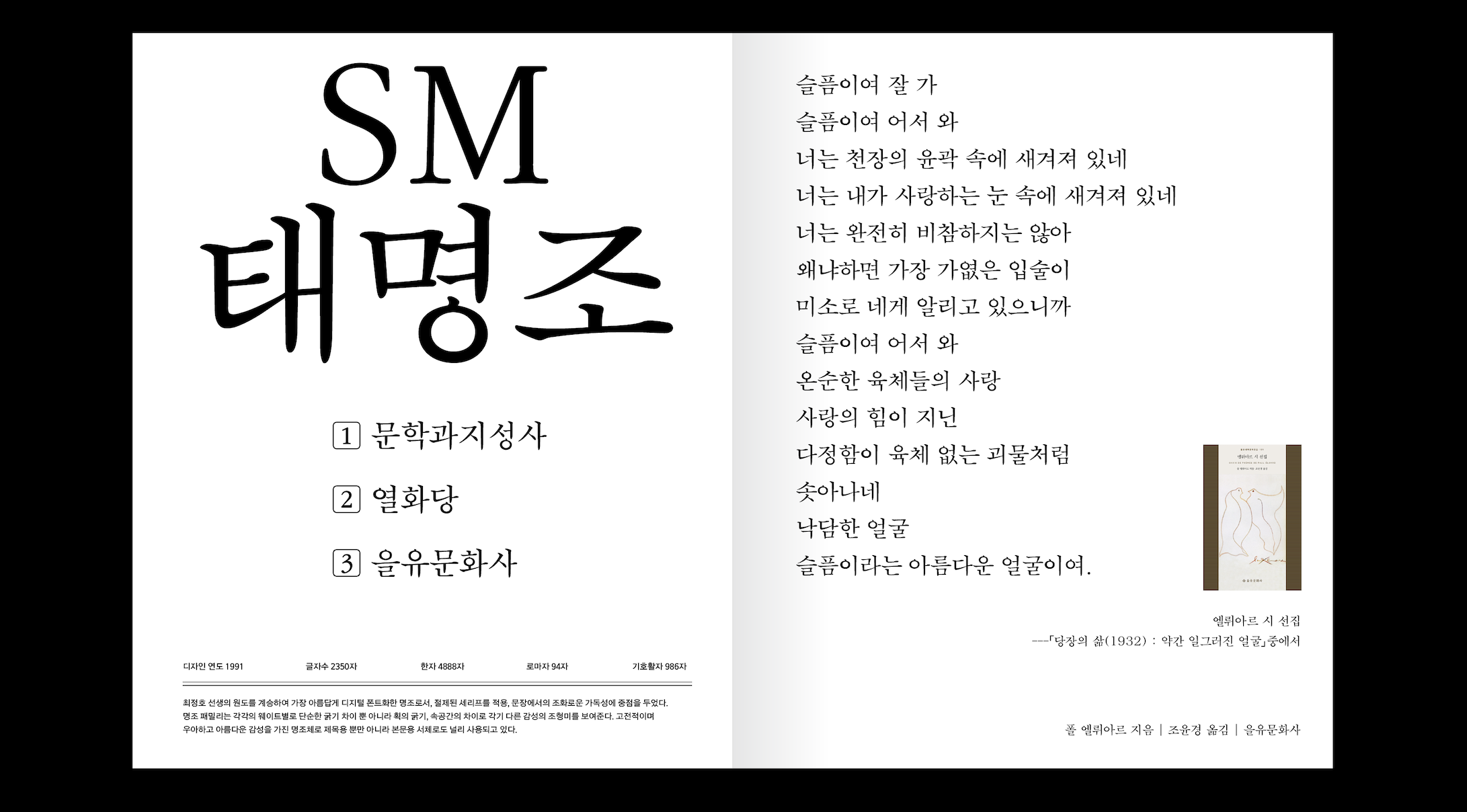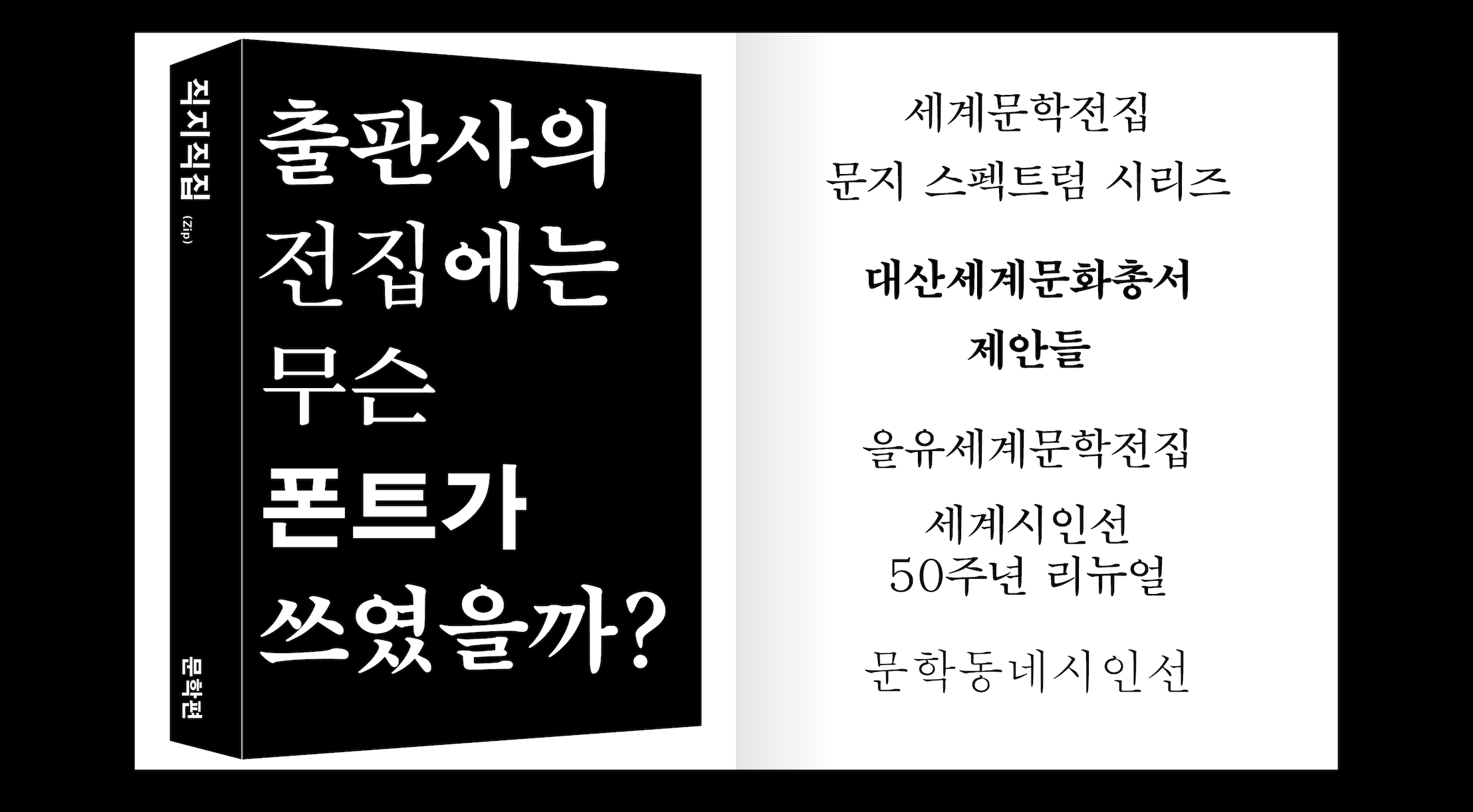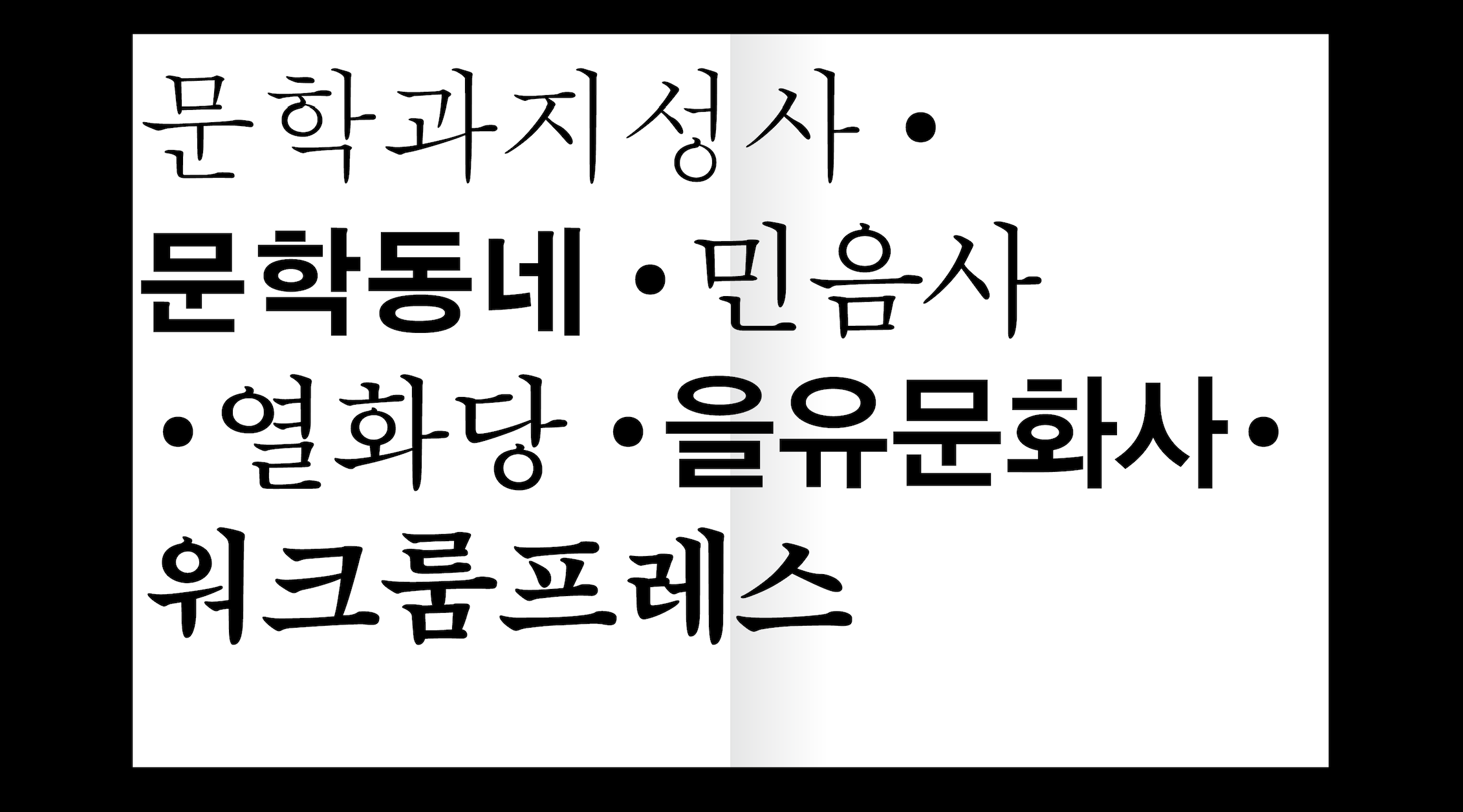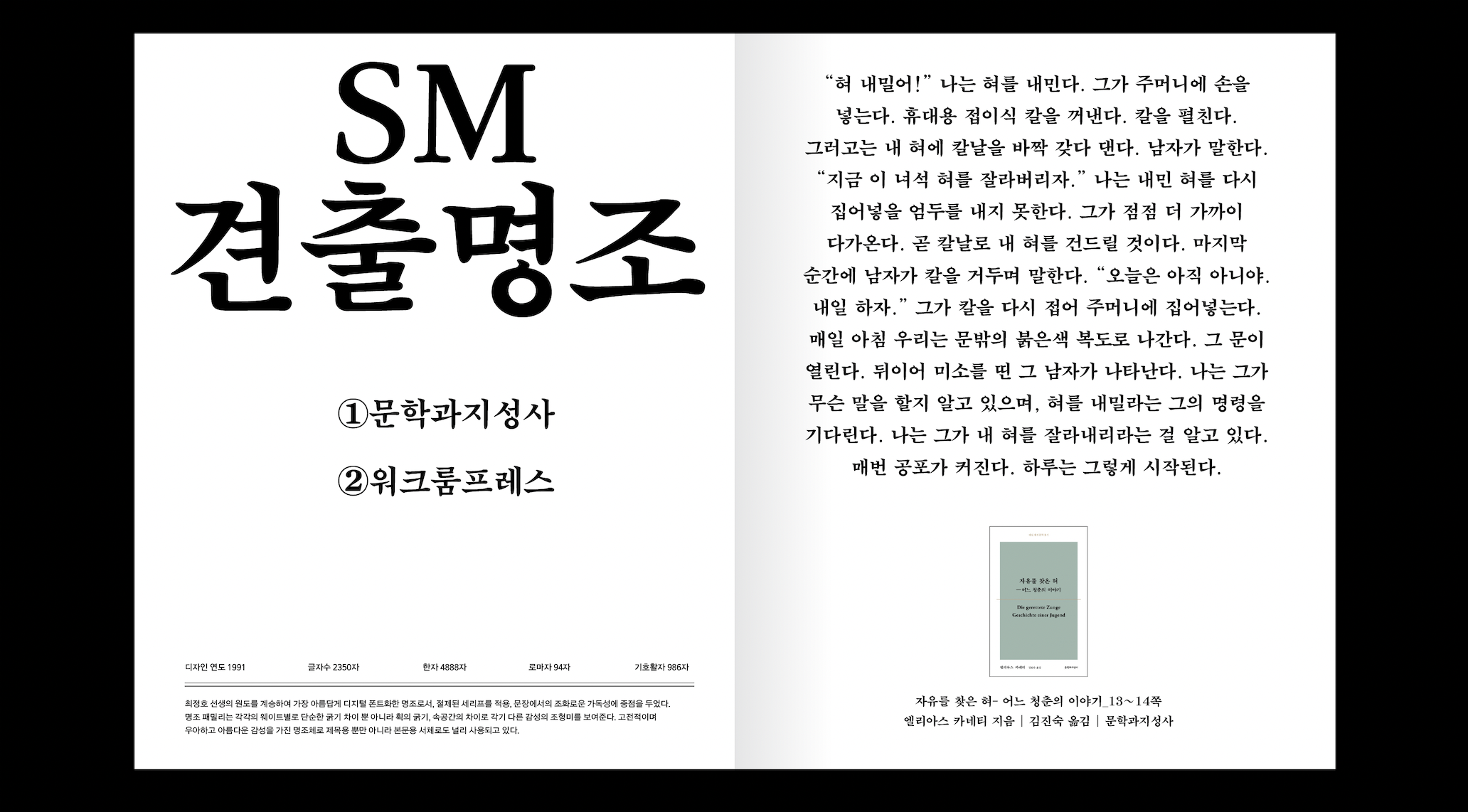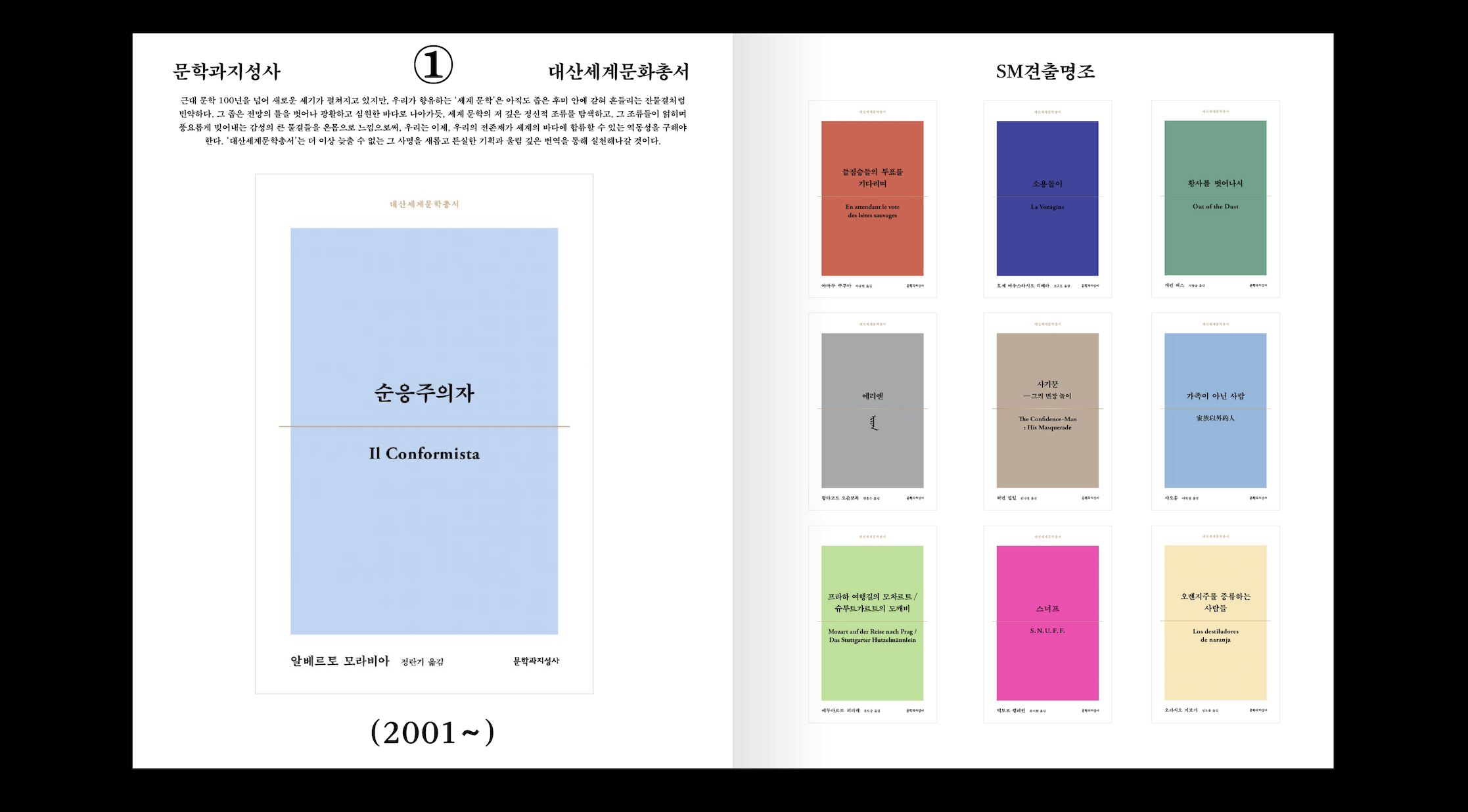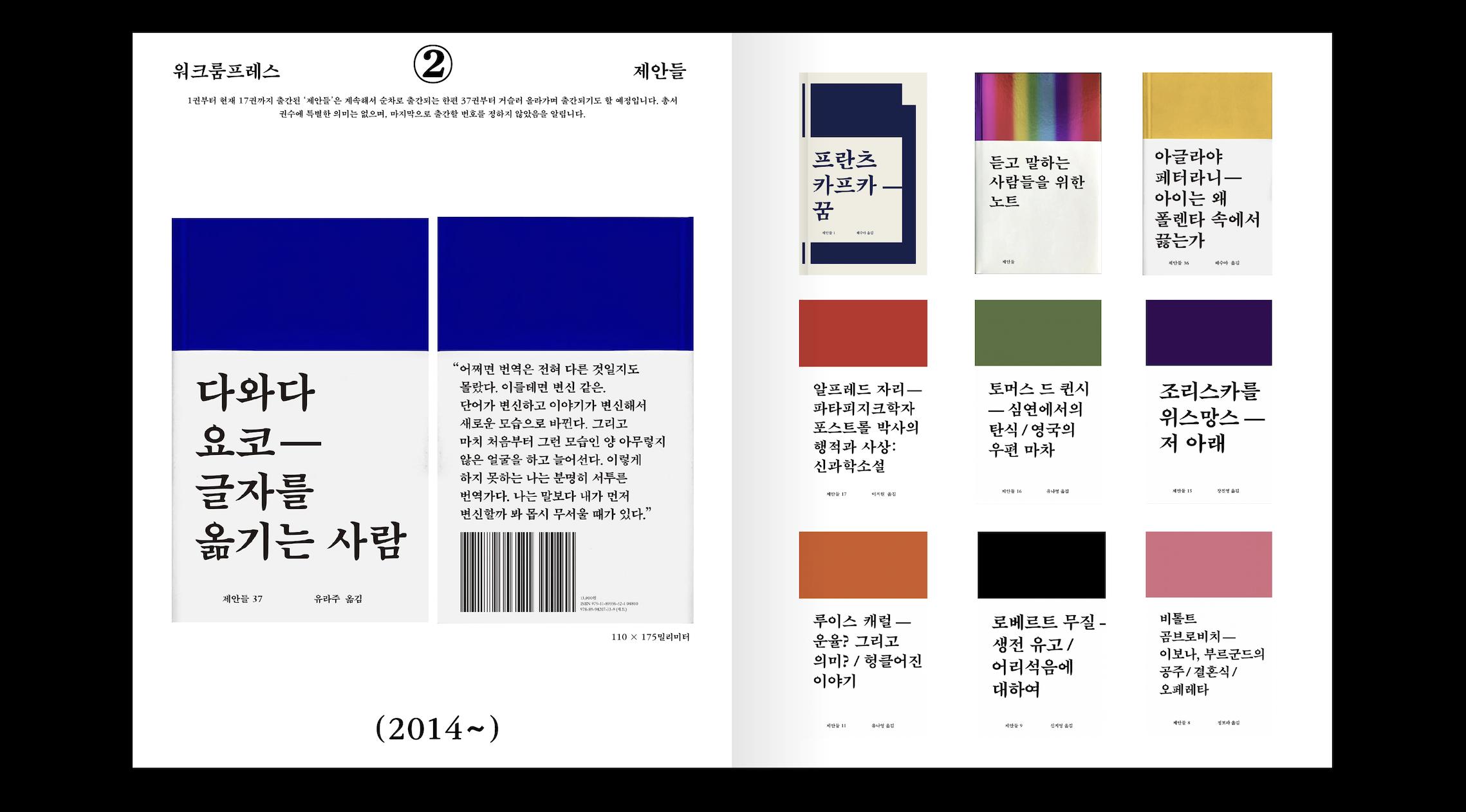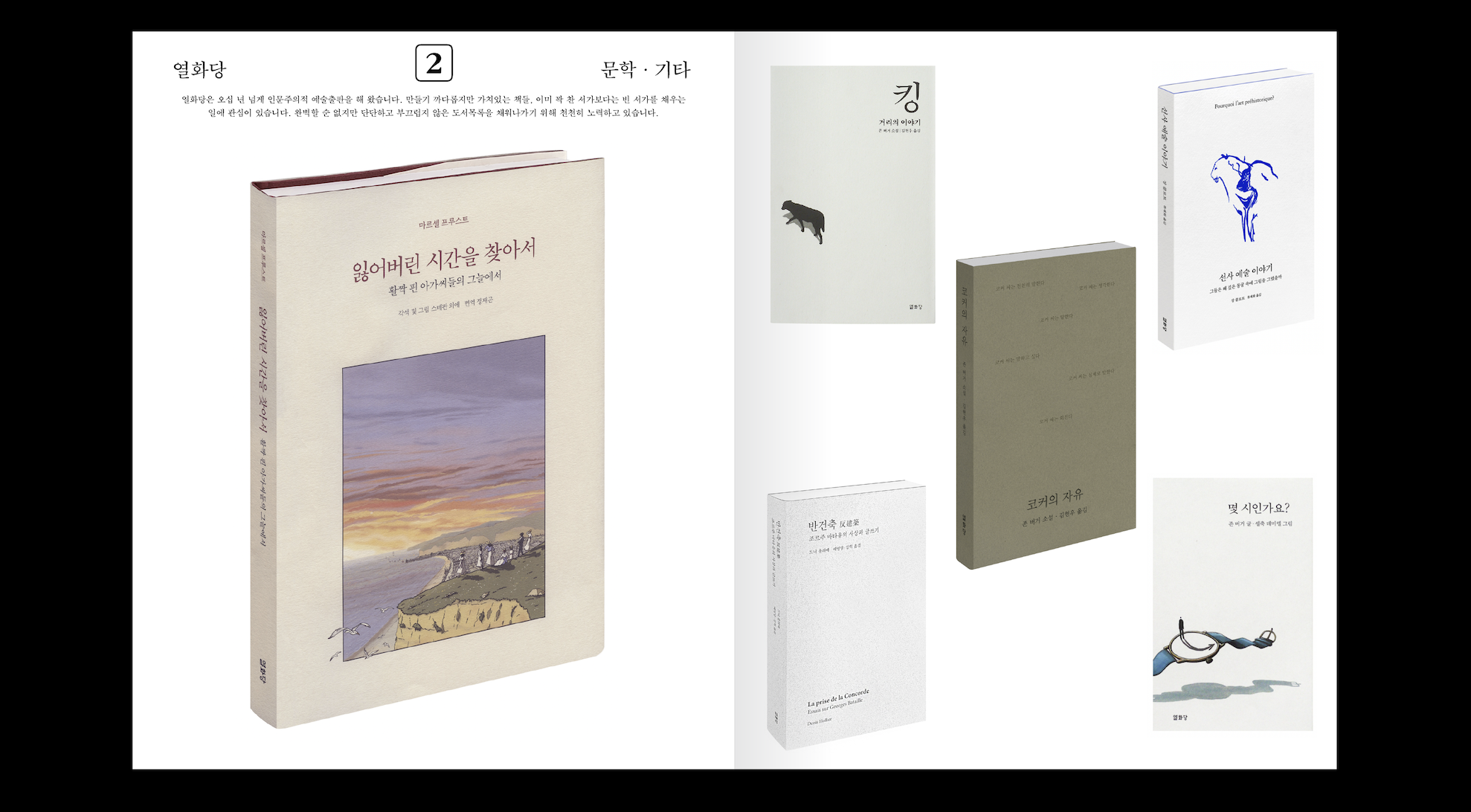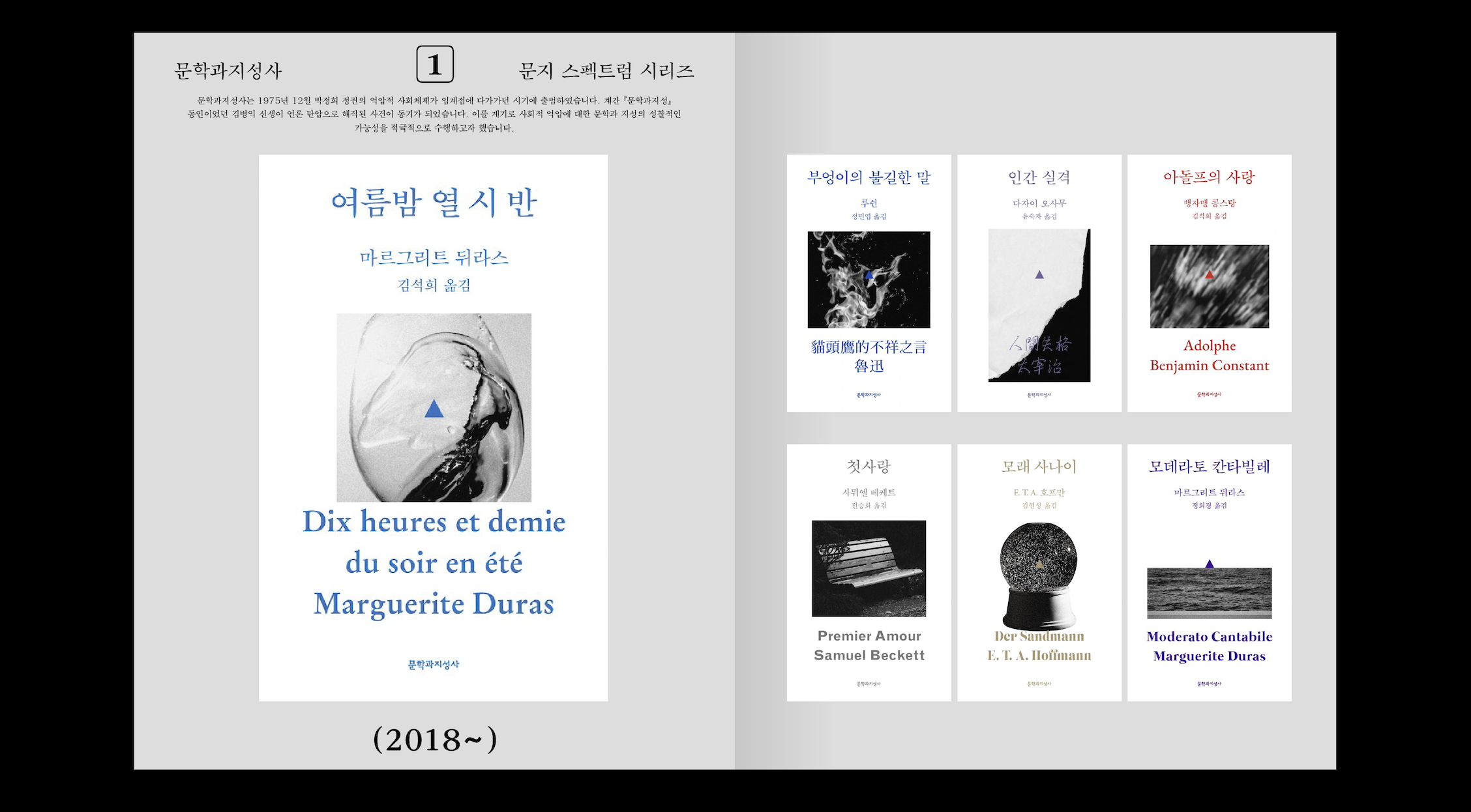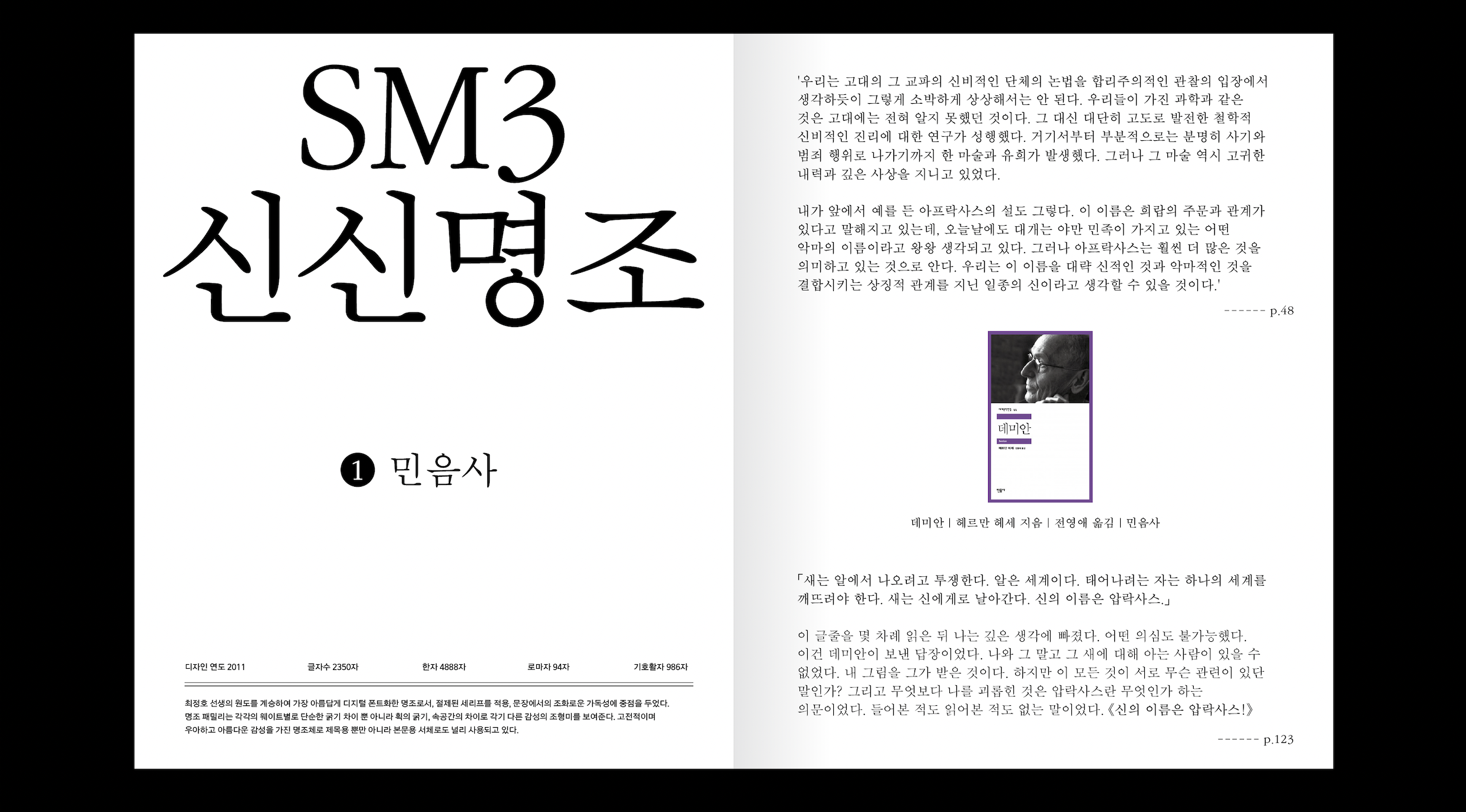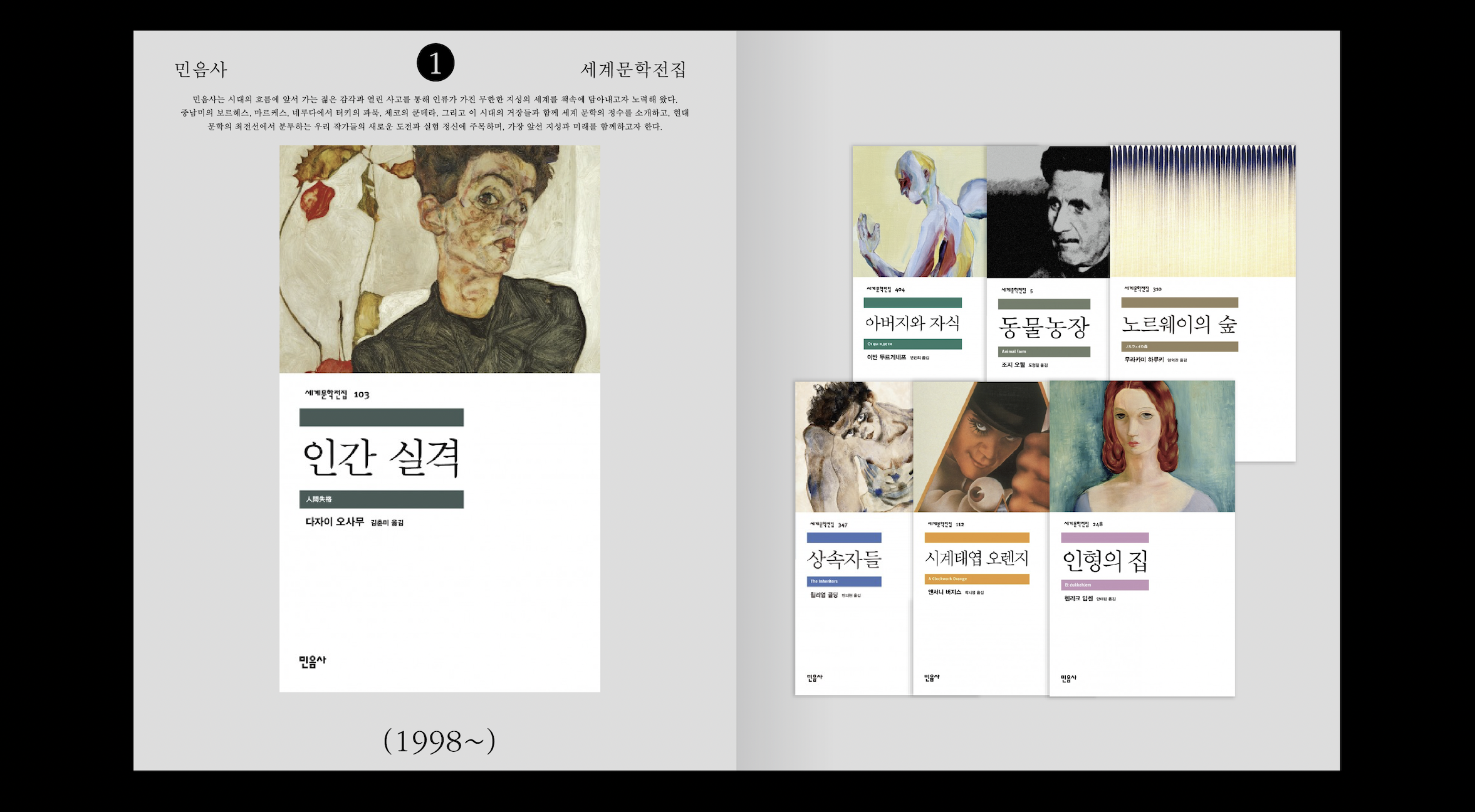
2023년 처음으로 등장한 직집(zip)은 직지폰트가 쓰인 디자인을 분야 별로 정리해 보여주는 콘텐츠 입니다.
2023년 시작을 알리는 직집(zip)은 무엇일까요?
오랜 시간 함께 해서 익숙한 것, 가장 가깝게 있으면서도 멀게도 느껴지는 것, 유아시절부터 노년까지 함께할 것.
바로 책! 입니다. 출판물에 특히나 사랑받는 직지폰트인데요, 이번에는 내방 한편에 어딘가에는 한 권 정도는 꼭 있을 굴지의 출판사들의 문학 전집을 소개합니다.
출판사 전집시리즈에는 무슨 폰트가 쓰였을까?
어렸을때부터 책장 한켠을 차지하고 있던 전집. 다들 기억 하시나요? 혹은 아직도 책장에 있을까요? 직지폰트는 꾸준하게 출판사와 라이센스 계약을 맺고 있습니다. 특히 SM클래식의 SM폰트는 책 표지와 본문에도 자주 쓰이고 있는데요. 이번 직집에서 90년도부터 현재까지 직지폰트 중 SM클래식 서체가 쓰인 문학 전집을 대표 서체 별로 모아봤습니다.
SM클래식은 직지소프트의 대표 서체 패밀리인 SM 클래식은 한글 글꼴의 아름다움을 절묘하게 표현하며 심미감으로 접목시킨 한글 글꼴 개발의 커다란 발자취를 남기신 최정호 선생의 원도로 만들어진 정통 서체 패밀리입니다. 1991년 출시부터 당시 사회의 역사적 순간과 문화를 기록해오고 있습니다. “SM클래식 폰트 시리즈는 한국 출판디자인의 역사의 증언, 과거와 현재를 연결하는 다리이다.”( 정재완 디자이너, SM클래식 탄생 30주년 인터뷰 중)
SM클래식 | SM견출명조
SM견출명조는 SM클래식 서체의 대표적인 명조체입니다. 가장 두꺼운 굵기로 주목도가 높아 제목용으로 디자이너에게 가장 많이 선택받고 있으며 고전적 인상, 진지함과 무게감을 줍니다. 컬러와 서체 두가지를 활용해 최소한의 요소로 강렬하게 디자인된 표지입니다.
문학과지성사 | 대산세계문화총서
문학과지성사는 1975년 12월 박정희 정권의 억압적 사회체제가 임계점에 다가가던 시기에 출범하였습니다. 계간 『문학과지성』 동인이었던 김병익 선생이 언론 탄압으로 해직된 사건이 동기가 되었습니다. 이를 계기로 사회적 억압에 대한 문학과 지성의 성찰적인 가능성을 적극적으로 수행하고자 했습니다.- ‘문지시인선’과 소설 등 문학 작품뿐만 아니라, 출판의 영역을 넓혀 약 3,000종의 문학, 인문, 학술, 청소년, 아동 분야의 서적들을 발행해왔습니다. (문학과지성사 소개글중)
워크룸프레스 | 제안들
2006년 12월 서울 창성동에서 시작한 그래픽 디자인 스튜디오 겸 출판사로 2013년부터 임프린트 작업실유령도 함께 운영하고 있습니다. 또 2014년 문학 총서 ‘제안들’을 시작으로 D. A. F. 드 사드 전집, 사뮈엘 베케트 선집, 한국 문학 총서 ‘입장들’등으로 그 범위를 넓히고 있습니다.
SM클래식 | SM태명조
SM태명조는 SM클래식 명조 계열 중에서 기분 좋은 긴장감과 매력을 담당하고 있습니다. 다른 SM 명조와는 다르게 ㅊ, ㅎ 의 첫 줄기가 주는 긴장감, 차별성이 큰 특징입니다. 앞서 SM견출명조가 컬러와 단독으로 쓰였다면 SM태명조는 이미지와 융합해 감각적인 표지 디자인을 보여줍니다.
열화당 | 문학
열화당은 오십 년 넘게 인문주의적 예술출판을 해 왔습니다. 만들기 까다롭지만 가치있는 책들, 이미 꽉 찬 서가보다는 빈 서가를 채우는 일에 관심이 있습니다. 완벽할 순 없지만 단단하고 부끄럽지 않은 도서목록을 채워나가기 위해 천천히 노력하고 있습니다.(열화당 소개글 중) 파주출판도시에 위치해 있는 열화당은 주로 미술서적을 다루며 폭넓은 예술서적을 출판하고 있습니다.
을유문화사 | 을유세계문학전집
1945년(을유년) 12월 1일, 광복의 감격과 의의를 기리며 ‘출판은 곧 건국 사업’이라는 사명감으로 첫발을 내디딘 을유문화사는 한국 현대사와 궤軌를 같이하며 한국 출판의 기틀을 다져 왔습니다.(을유문화사 소개글 중) 역사가 깊은 을유문화사는 오늘날 『국화와 칼』, 『이기적 유전자』, 『러셀 서양철학사』, 『도시는 무엇으로 사는가』, 『글자 풍경』 등 단행본과 50년 만에 새롭게 선보이는 ‘을유세계문학전집’, 시공을 초월한 지적 성취를 담은 ‘을유사상고전’, 위대한 예술가들의 삶과 작품 세계를 조명한 ‘현대 예술의 거장’ 등 시리즈를 출간하고 있습니다.
SM클래식 | SM3신신명조
SM클래식 패밀리에서 가장 널리 사용되는 신신명조는 본문용에서부터 제목용까지 어디에든 사용되면 그 역할을 완벽한 역할을 해내는 폰트입니다. ‘공기같은 폰트’ 라는 별명을 가졌을 만큼 가장 익숙하고 친숙한 폰트입니다.
민음사 | 세계문학전집, 세계시인선_50주년 리뉴얼
민음사는 백성의 올곧은 소리를 담는다는 정신을 근간으로 1966년 5월 19일 설립되었다. 이후 몇십 년의 급변하는 역사 속에서도 새로운 문학과 참된 지성의 세계를 끊임없이 탐색하며 오늘에 이르렀다. - 민음사의 대표적인 시리즈 [오늘의 시인 총서]와 [오늘의 작가 총서]는 그 자체로 한국 문학사를 그려내며 20세기 이후 대표적인 작가와 시인들의 초상을 보여 준다. [민음의 시]는 지난 20여 년간 한국 시단을 이끌어 온 중견 시인들을 배출해 왔으며 미래 한국 시단을 이끌어 갈 젊은 목소리에 꾸준히 주목하고 있습니다.(민음사 소개글 중)
SM클래식 | SM3세명조
SM클래식 명조 중에서 가장 가는 굵기인 세명조는 붓의 특성이 가장 잘 표현되어 섬세한 아름다움 보여줍니다. 책표지의 굵은 서체는 SM견출명조로 세명조와 대비를 이루고 있습니다. 표지와 서체 컬러의 대비와 굵기의 대비로 미니멀하게 디자인된 표지입니다.
문학동네 | 세계시인선
1993년 12월 첫걸음을 내디딘 문학동네는 문학 전문 계간지 『문학동네』를 창간하며 이후 역량 있는 신인작가들을 발굴하고 당대를 대표하는 작가들의 작품을 지속적으로 펴냄으로써 한국 문단의 새로운 흐름을 형성했습니다. 신생의 기운으로 팽팽하게 긴장되어 있는 곳, 새롭고 신선하며 탄력이 넘치는 곳, 문학 본연의 아름다움과 문학의 자존을 지켜나가는 출판사입니다.(문학동네 소개글 중)